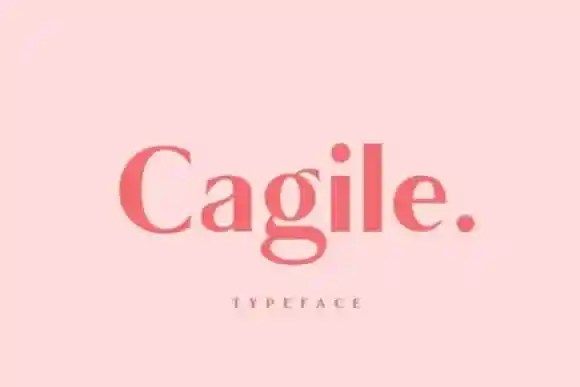
Cagile Sans Serif Font – Download Grátis
A Cagile Sans Serif é uma fonte sans-serif que apresenta múltiplas pesos, criada e compartilhada por JavaPep. Esta elegante fonte sem traços é versátil o suficiente para se adaptar a uma ampla gama de projetos. Suave e simples em sua natureza, ela tem a capacidade de se tornar uma escolha favorita, adequando-se perfeitamente a editoriais, identidades corporativas, criação de logos, design web, embalagens, redes sociais e muito mais. Com suas características limpas e modernas, a Cagile Sans Serif é ideal para projetos que buscam um equilíbrio entre elegância e simplicidade. Seja em uma situação formal ou casual, esta fonte oferece uma escolha segura e profissional para personalizar seu trabalho. A sua versatilidade significa que ela pode ser usada com sucesso para criar designs atraentes em muitos diferentes contextos, tornando-a um aliado valioso para qualquer designer gráfico.